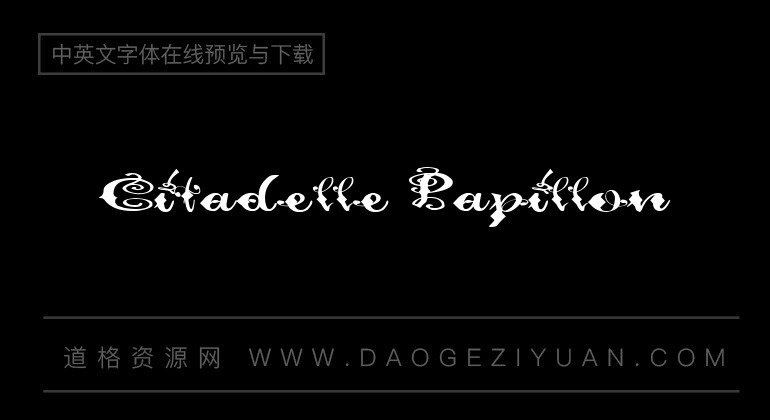
? Citadelle Papillon 是一款有趣而优雅的字体,它具有温暖的感觉,可以为您的设计提供一种美丽而精致的外观。它有着优雅的花纹,可以营造出大方而高雅的氛围,是一款非常适合用于设计海报、书籍封面、卡片等的字体。它的细节极其精致,可以帮助您让设计更加精致。内容介绍
Citadelle Papillon是一款非常不错的手写艺术字体,具有很好的视觉感,适合于文化类的宣传设计、商业类品牌的广告和产品包装设计以及个性化文字排版等较多场景。